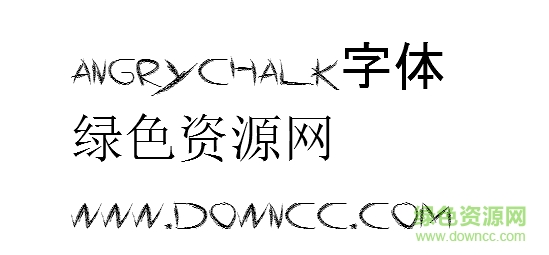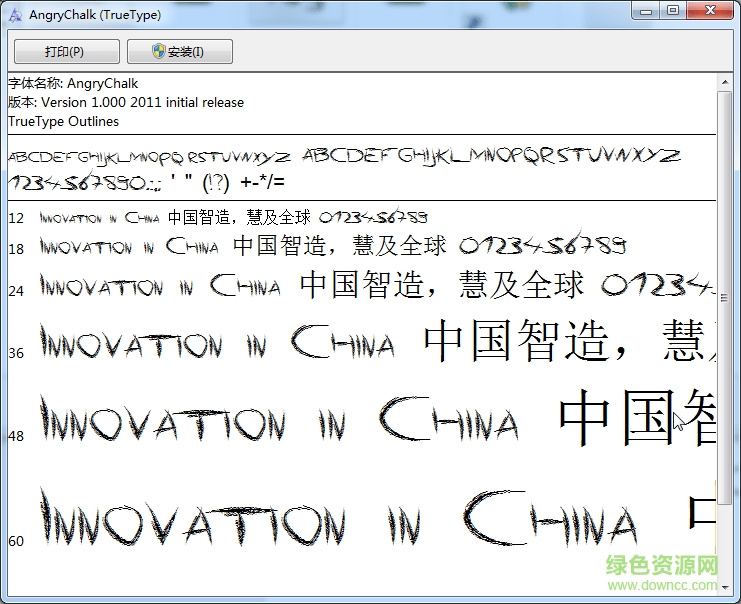
angrychalk(粉筆字體)
angrychalk是一款有著獨(dú)特藝術(shù)效果的粉筆字體,像用粉筆勾畫出來的字體圖案,讓設(shè)計(jì)顯得簡單卻有著獨(dú)特內(nèi)涵,喜歡的朋友就可以來綠色資源網(wǎng)體驗(yàn)哦!
angrychalk字體介紹
angrychalk,直譯為生氣的粉筆,字跡如同粉筆在黑板上書寫所致,有著獨(dú)特的藝術(shù)字體書寫風(fēng)格和簡明大方的造型設(shè)計(jì),可以適用于書面設(shè)計(jì)、海報(bào)設(shè)計(jì)、校園主題設(shè)計(jì)等場合。